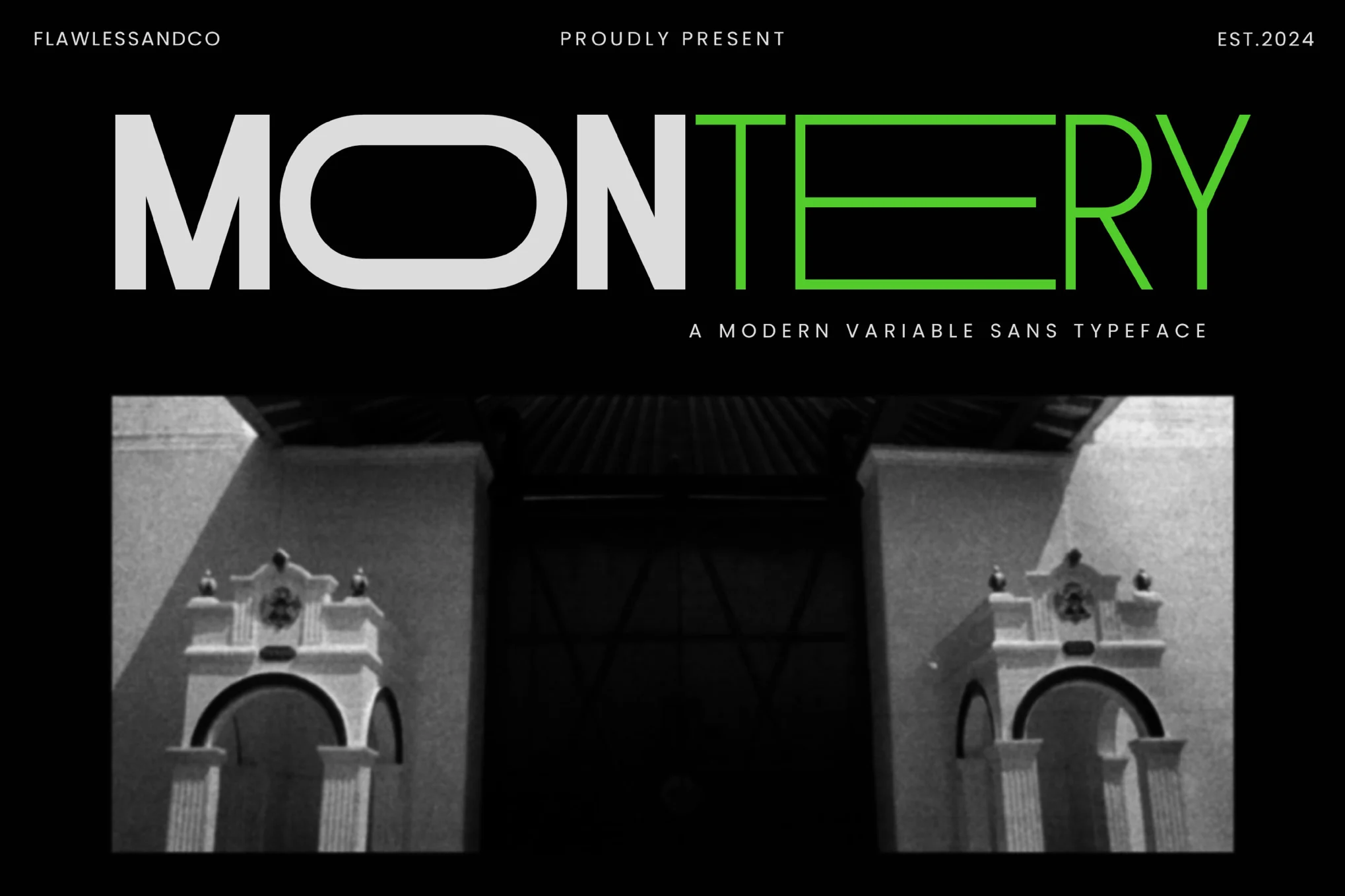
دانلود فونت Montery – Sans Serif Family Typeface
معرفی “Montery”، یک خانواده فونت sans serif شیک و همه کاره که برای رفع نیازهای طراحی مدرن طراحی شده است. مونتری با خطوط تمیز، اشکال پویا و وزنهای متغیر، برای ایجاد طرحهای حرفهای و معاصر که به انعطافپذیری و سبک نیاز دارند، عالی است.